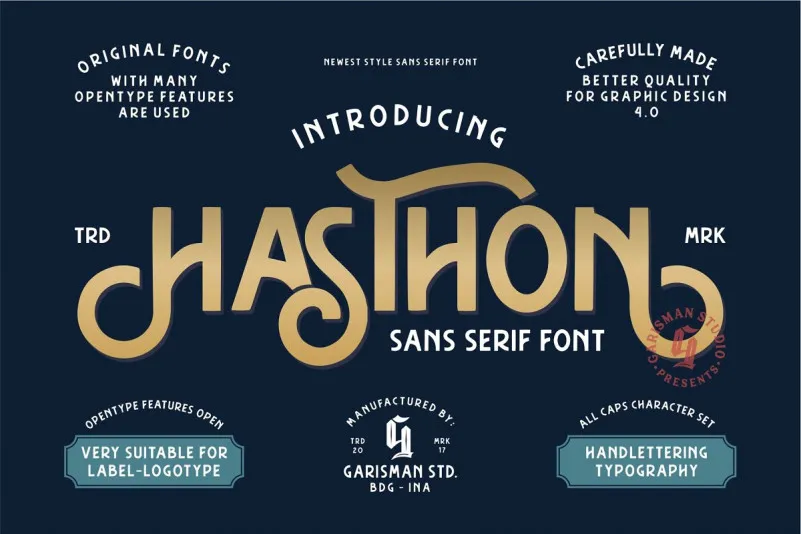
Hasthon Vintage Font – Download Grátis
A fonte Hasthon Vintage é perfeitamente adaptada para criar designs que transmitem uma sensação vintage clássica, tradicional e trabalhada à mão. Introduzida pela designer 24Design, ela traz um toque de sofisticação aos projetos tanto da arquitetura tradicional quanto da contemporânea. Este tipo-fonte elegante é perfeito para criar títulos únicos e logomarcas que exibem uma aparência luxuosa e fashionista. A Hasthon Vintage Font já vem com codificação PUA, o que a torna especialmente adequada para quem procura um estilo vintage em seus projetos. Seja para materiais de marca, camisetas impressas, cartões de papelaria, logos, posters ou fotografias, a Hasthon Vintage é uma excelente escolha para qualquer tipo de projeto gráfico. Além disso, ela também se adequa perfeitamente aos desafios do design em t-shirts e para o trabalho com imagens, transformando seus designs digitais em algo realmente único.